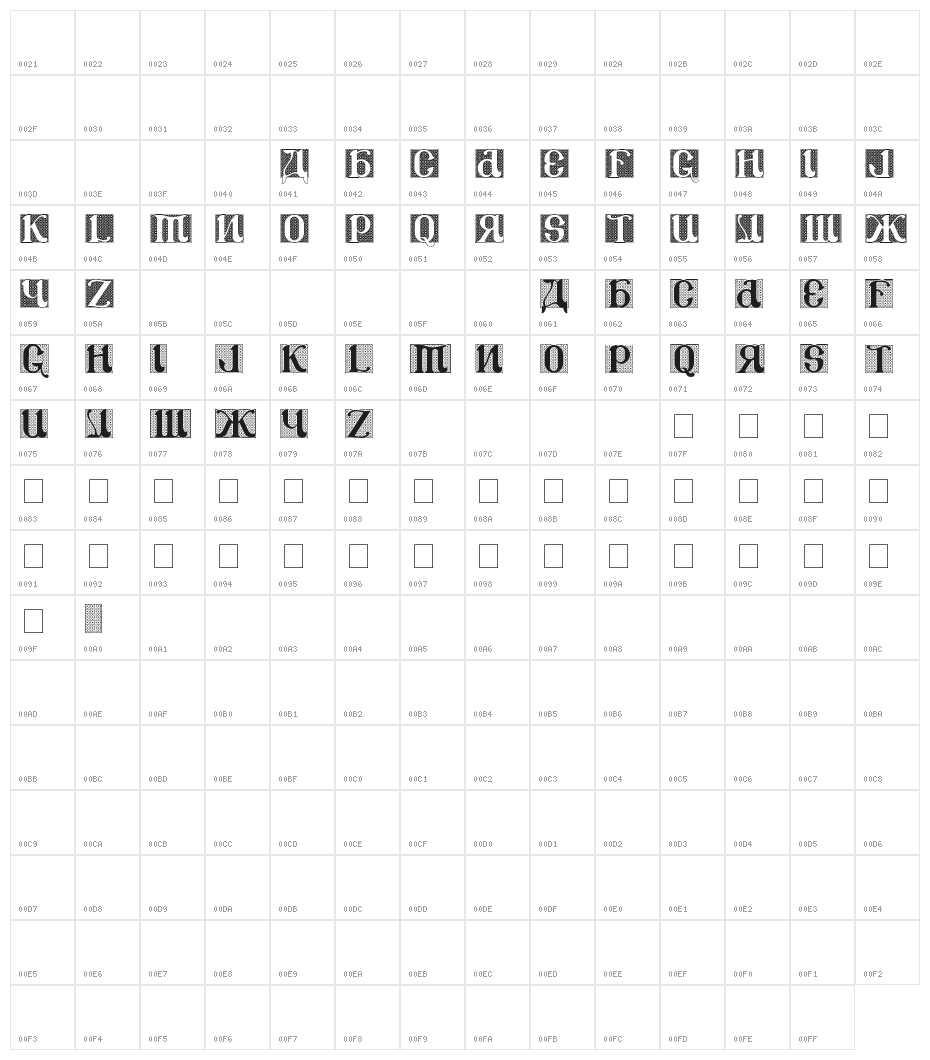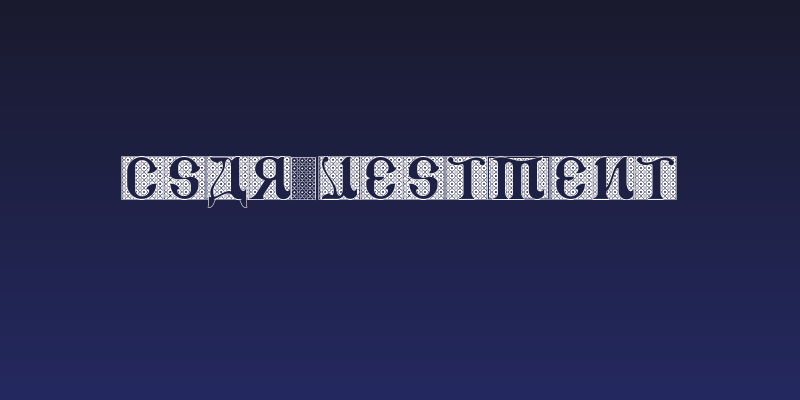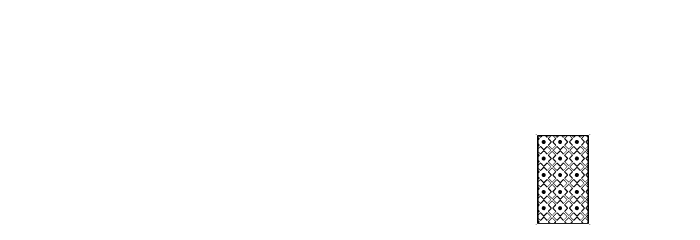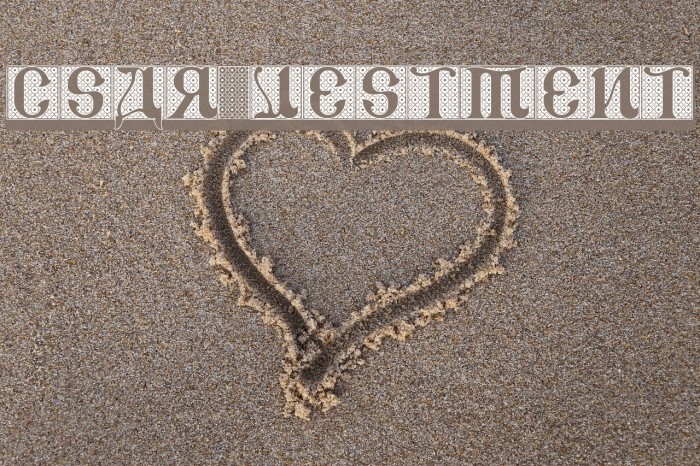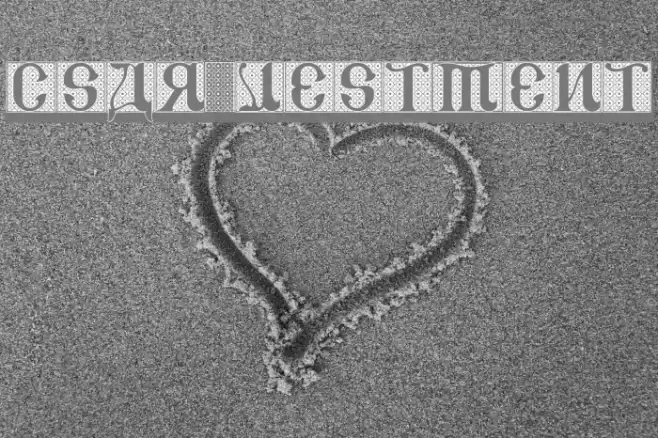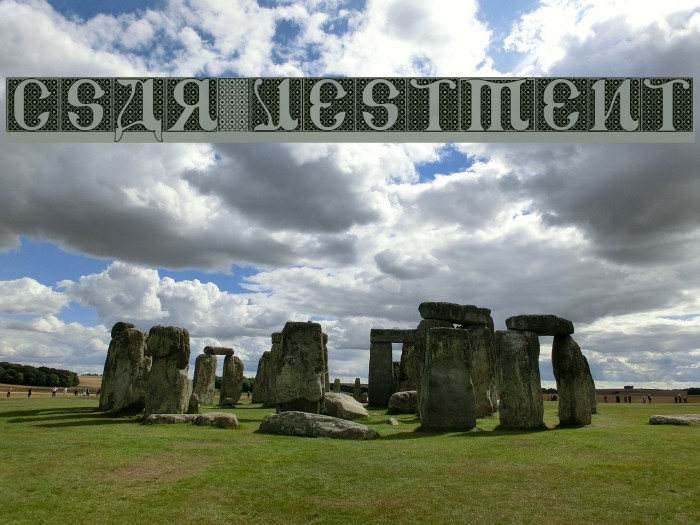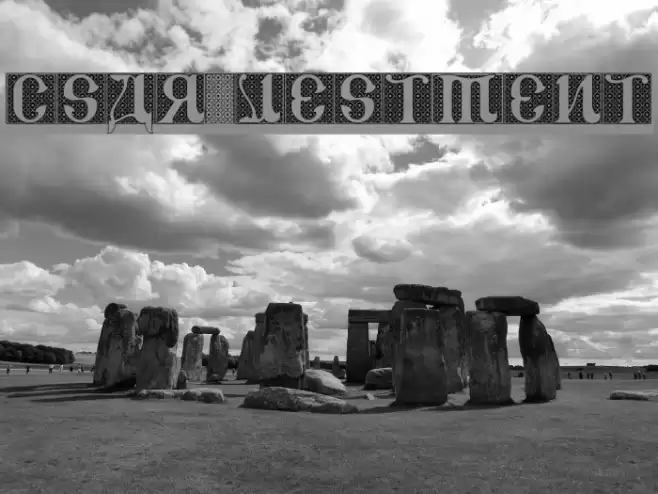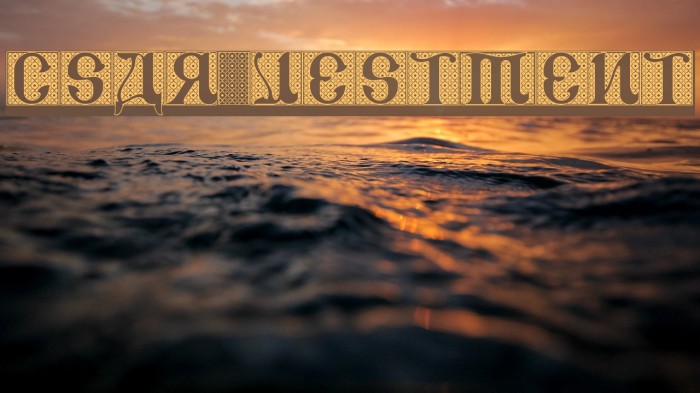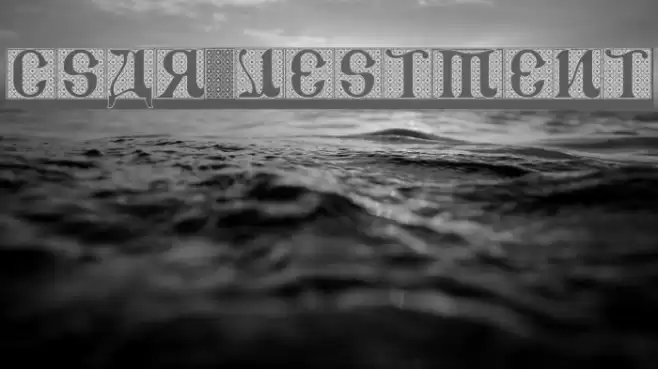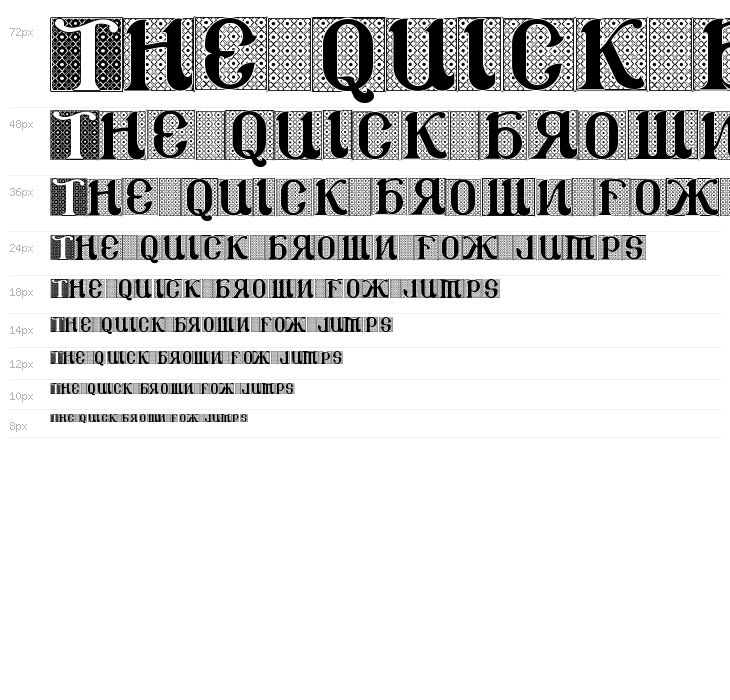
CSAR VESTMENT Font
| حالة الاستخدام | Headlines, Logos, Invitations |
| مشاريع مقترحة | Ideal for use in invitations, posters, branding for luxury products, or any project that requires a touch of elegance and historical flair. |